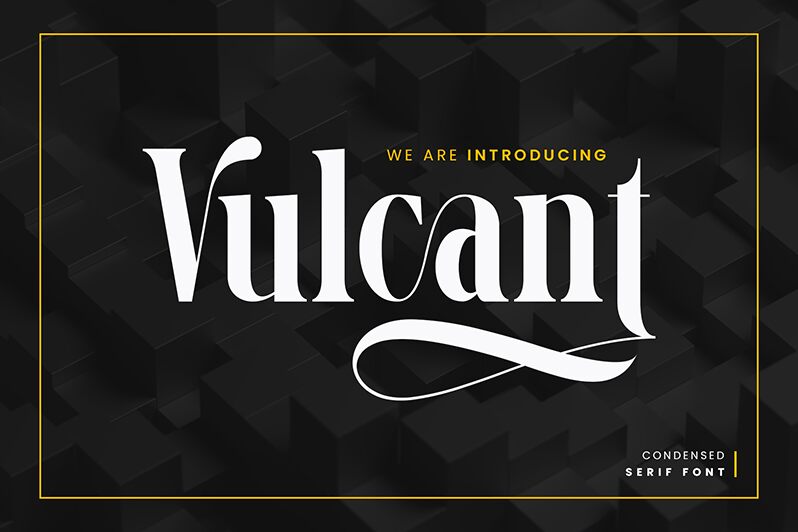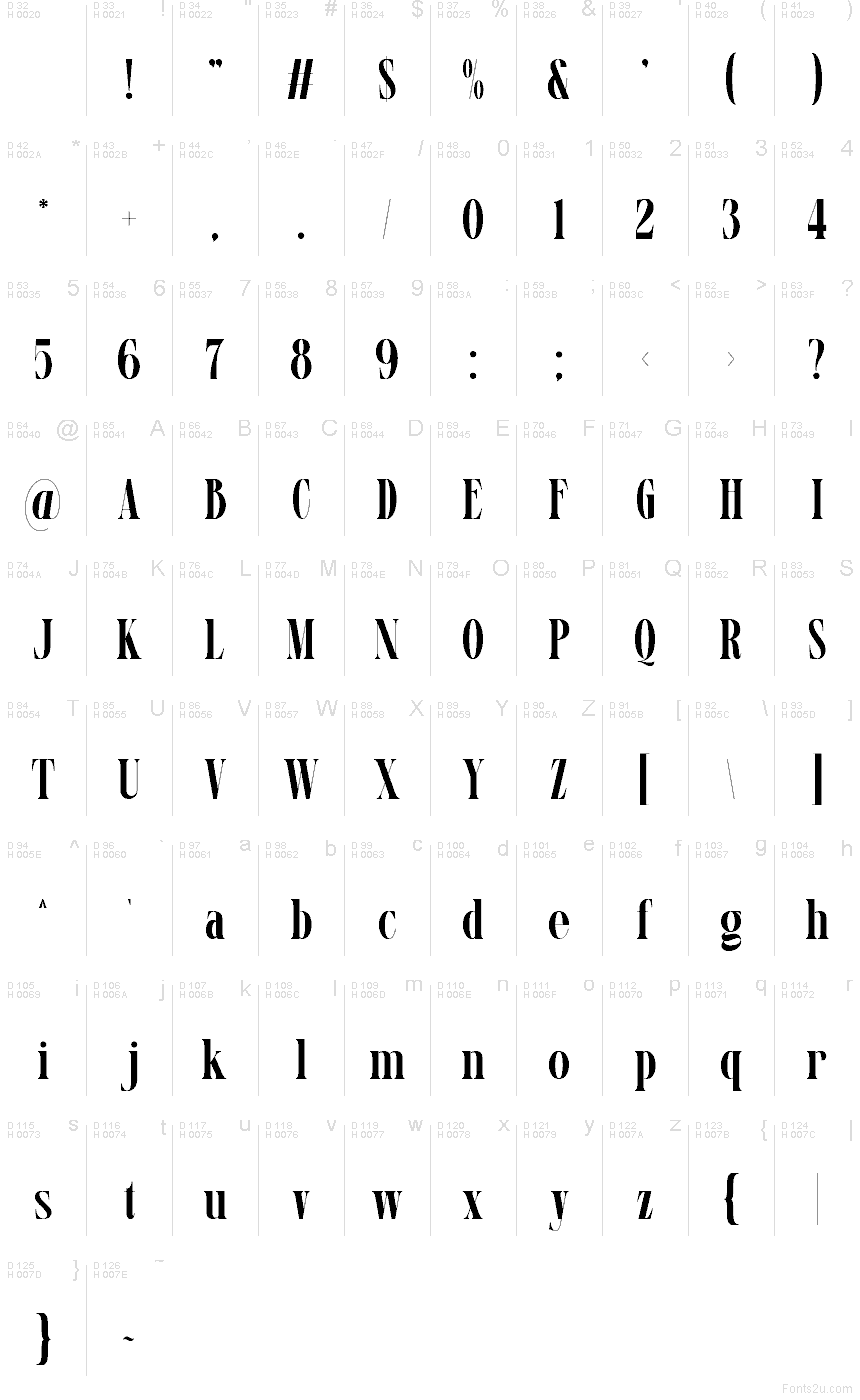
Vulcant von SlideShoot ist eine kostenlose Serifenschrift mit hohem Kontrast und dem Flair eines Fashion-Magazins. Ihre Buchstaben kombinieren lange, sich verjüngende Striche mit kompakten Kurven und scharfen Übergängen. Das verleiht der Schrift einen gefassten, leicht dramatischen Rhythmus, der eher an Magazin-Titel erinnert als an klassische Buchsatz-Serifen.
Sie eignet sich hervorragend für Branding, Beauty-Verpackungen, Plakat-Überschriften, Cover-Lines und Restaurant-Menüs, bei denen Eleganz auf Klarheit trifft. Als kostenloser Font eignet sich Vulcant auch gut für kurze Logos, Titelkarten und Initialen im Monogramm-Stil, da der Kontrast und die schmalen Kurven selbst kurzen Wörtern eine raffinierte, elegante Präsenz verleihen.